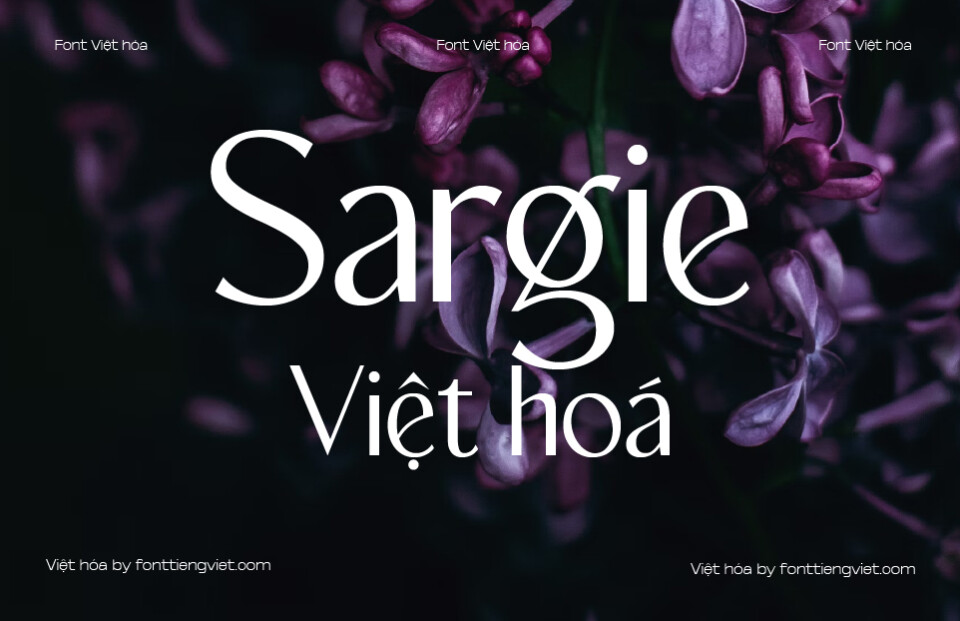
Font Việt hóa 1FTV VIP Sargie
Font Việt hóa 1FTV VIP Sargie – Bộ Font Chữ Nghệ Thuật Đẳng Cấp Cho Thiết Kế
Giới thiệu về Font Việt hóa 1FTV VIP Sargie trong thiết kế đồ họa
Trong thế giới sáng tạo ngày nay, việc lựa chọn một bộ Font Miễn Phí chất lượng luôn là ưu tiên hàng đầu của các nhà thiết kế. Font Việt hóa 1FTV VIP Sargie nổi lên như một hiện tượng nhờ sự kết hợp hoàn hảo giữa nét cổ điển và hơi thở hiện đại. Đây là bộ font được tinh chỉnh kỹ lưỡng để phù hợp với bảng mã tiếng Việt, giúp người dùng không còn lo lắng về lỗi hiển thị dấu khi soạn thảo văn bản hay thiết kế ấn phẩm truyền thông. Với đường nét thanh mảnh nhưng vô cùng dứt khoát, bộ font này mang đến một cảm giác sang trọng, chuyên nghiệp và đầy tính thẩm mỹ cho mọi dự án từ học đường đến doanh nghiệp.
Những đặc điểm nổi bật của bộ Font Việt hóa 1FTV VIP Sargie
Phong cách thiết kế độc đáo và linh hoạt
Font Việt hóa 1FTV VIP Sargie sở hữu cấu trúc ký tự độc đáo với những đường cong mềm mại xen lẫn các góc cạnh tinh tế. Điều này giúp bộ chữ có khả năng ứng dụng cực kỳ linh hoạt. Bạn có thể sử dụng nó cho các tiêu đề lớn của tạp chí, poster phim, hoặc thậm chí là các thiết kế logo đòi hỏi sự phá cách. Đặc biệt, các ký tự dấu tiếng Việt được thiết kế hài hòa, không làm mất đi cấu trúc nguyên bản của font gốc, đảm bảo tính thẩm mỹ cao nhất cho người xem.
Tối ưu hóa cho người dùng tại Việt Nam
Sự khác biệt lớn nhất của Font Việt hóa 1FTV VIP Sargie chính là khả năng hiển thị mượt mà trên nhiều phần mềm thiết kế phổ biến như Adobe Photoshop, Illustrator hay Canva. Đội ngũ kỹ thuật đã tiến hành căn chỉnh khoảng cách giữa các chữ cái (kerning) một cách chuẩn xác, giúp đoạn văn bản trông cân đối và dễ đọc hơn. Đối với các bạn học sinh, sinh viên đang tìm kiếm sự mới mẻ cho bài thuyết trình hoặc thiết kế báo tường, đây chắc chắn là một sự lựa chọn không thể bỏ qua để tạo nên điểm nhấn riêng biệt.
Ứng dụng thực tế của Font Việt hóa 1FTV VIP Sargie
Không chỉ dừng lại ở các sản phẩm in ấn, Font Việt hóa 1FTV VIP Sargie còn hoạt động rất tốt trên nền tảng kỹ thuật số. Bạn có thể dùng font này để làm ảnh bìa Facebook, thumbnail YouTube hay các bài đăng trên Instagram để thu hút sự chú ý của người theo dõi. Với phong cách VIP đặc trưng, bộ font giúp nâng tầm giá trị hình ảnh, biến những nội dung đơn giản trở nên nghệ thuật và lôi cuốn hơn bao giờ hết. Việc cài đặt font cũng rất đơn giản, chỉ cần vài thao tác giải nén và cài đặt vào hệ thống là bạn đã sẵn sàng để sáng tạo.
Kết luận về bộ Font Việt hóa 1FTV VIP Sargie